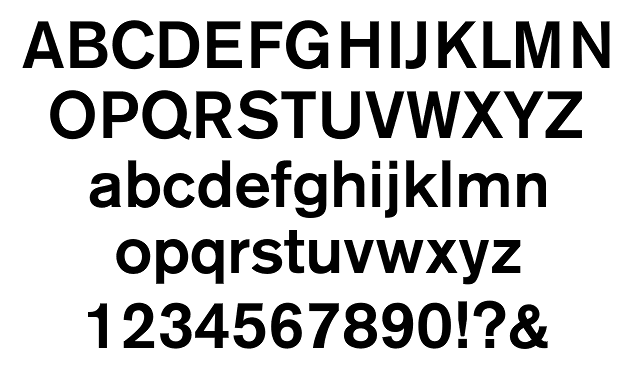
Гротеск — шрифт рубленый. Примеры
Работая над собственным сайтом, пользователи сталкиваются с огромным количеством вопросов. Помимо технической составляющей, много времени приходится уделять юзабилити. А тут вопрос еще сложнее, поскольку характеристика субъективная, кому-то нравится определенный цвет, кому-то легче читать шрифт «Гротеск». Чтобы все это учитывать, следует ответить себе на кучу вопросов.
Проблемы
Вообще, выбор шрифтов довольно тонкое дело. Существует ряд стандартов, которые требуют от дизайнера следовать правилам. Часть из них лучше применять, остальными можно пренебречь. Некоторые стандарты устарели и не соответствуют нынешним требованиям. Рядом с ними появляются новые правила, соответствующие веяниям моды.
Чтобы для собственного блога или коммерческого сайта выбрать определенный стиль шрифта, придется учитывать и тематику, и назначение ресурса. Разобраться в их создании и некоторых стилях.
Шрифт
Что такое шрифт? Толкований немного – два.
Оба передают основную суть. Это графическое отображение начертания знаков и букв, которые объединены унифицированной стилистикой и композицией. В типографии понятием называют литеры, используемые в наборе.
Тут же стоит упомянуть о гарнитуре. Это единый стиль шрифта, его особое оформление, одинаковое очертание, относимое к группе с разными видами и кеглем.
Тип
Классифицировать шрифты можно по разным признакам. Чаще всего их разделяют графически. Тут рассматривается контрастность, размер, внешний вид засечек. По этим критериям существует шесть групп:
- С малым контрастом без засечек называются рубленными.
- Среднеконтрастные со слегка увеличенными вертикальными штрихами.
- Средняя контрастность, мелкие засечки, похожие на треугольники и округленные буквы с наклоном, назвали медиевальным типом.
- Контрастные штрихи, тонкие длинные засечки, объединены с вертикальными, ось округлостей вертикальная – обыкновенный тип.
- Малоконтрастный, длинные утолщенные засечки, основные штрихи объединенные с закруглениями – брусковой тип.
- Длинные утолщенные засечки, закругленные концы, основные штрихи с прямыми углами и закруглениями – новый малоконтрастный шрифт.
Это не все типы шрифтов. Есть такие вариации, которые сильно разнятся от привычных нам. Они объединены в особые группы.
Компьютерные
Говоря о шрифтах, нельзя забывать и о компьютерных. Они представлены специальным файлом, который описывает буквенные, цифровые, служебные и псевдографические символы. Используется для визуализации этих знаков в программе или ОС.
Сюда относятся и шрифты для Word. Хотя помимо набора символов, над которым работал художник, может подразумеваться файл, либо, как уже упоминалось ранее, комплекс металлический литер.
Дизайнеры часто употребляют слово «фонт», которое с английского переводится как шрифт, но именует конкретно компьютерную его версию. Может заменять название файла со шрифтом либо понятие «гарнитура».
Типология
В этом случае типология несколько отличается от ранее описанной.
Типы шрифтов могут различать по внутреннему устройству, ширине или применению.
Если упоминают ширину символов, то различают моноширинные или пропорциональные шрифты. В первую группу относят символы с одинаковой шириной. То есть независимо от гарнитуры присутствует однозначность в размещении символов на дисплее. Помимо положительных черт, эта группа имеет и отрицательные характеристики. К примеру, наблюдаются проблемы с визуализации широких букв типа «Ш», заметна увеличенная ширина набора, а рисунок знака неравномерный.
К пропорциональным относят символы с разной шириной. Отличается этот тип тем, что читателю его комфортно воспринимать. Он выглядит аккуратно в текстовом массиве и почти всегда применим в печати.
По применению выделяют три группы, в которых можно увидеть шрифты для Word. Есть моноширинные, без засечек и с ними. Каждый получил свое особое имя: Mono, Sans и Serif соответственно.
Как уже говорилось ранее, типы эти есть в Word и подобных текстовых процессорах, также в веб-дизайне, графическом интерфейсе и т.
д. Mono используют для визуализации исходного кода и чисел. С засечками символы лучше воспринимаются при чтении на высоких показателях DPI. Без засечек шрифт рекомендуют использовать для заголовка, важных пометок, текстовых фрагментов. К этому типу и относят «Гротеск».
Компьютерные типы шрифтов относительно внутреннего устройства бывают растровые и векторные. Первый вариант представлен визуализацией символов с помощью пикселей, второй – математических формул.
«Гротеск»
Так мы подобрались к одному из типов шрифтов. Этот вариант на английском называется «sans serif», переводится на русский как «без засечек». Впервые подобный набор реализовали в 1816 году. Его использовали в рекламе. Шрифт «Гротеск» стал известен благодаря неизвестному творцу.
Важно понимать, что вариантов «Гротеска» большое количество. Они получили популярность в 20 веке. Тогда их начали активно применять для привлечения внимания. Хотя иногда использовали и в текстовом наборе. Среди рубленых шрифтов известными стали «Готик», «Гельветика», «Универс».
В то время как Eastman Compressed и Eastman Condensed ведут себя как компактные семейства, Eastman Grotesque адаптирует стиль дизайна семейства к гуманистическим пропорциям. Все они имеют прочный монолинейный дизайн и высокую высоту по оси x, что делает основной текст, установленный в Eastman, чрезвычайно удобочитаемым на бумаге и на экране.